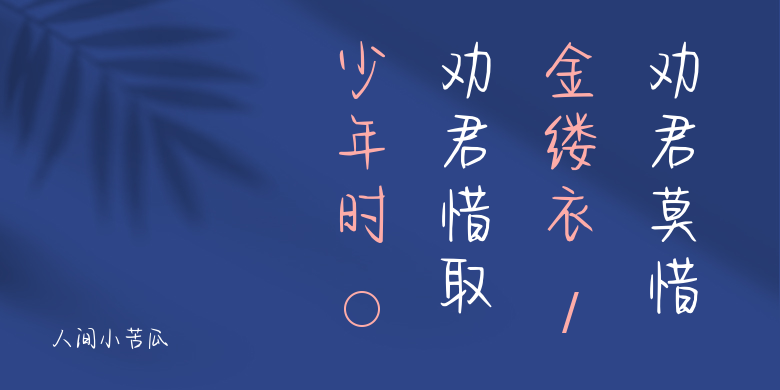
人间小苦瓜
人间小苦瓜,这款字体结构工整、笔画清晰,兼顾美观与易读性,适用于标题、正文、海报、包装、LOGO 等多种场景。字形优雅稳定,风格百搭耐看,适配日常排版与创意设计,让文字呈现更舒适、更具质感。人间小苦瓜一笔一画,皆是细节,以均衡的比例、流畅的线条打造舒适视觉体验,字形端正大气,风格简约现代。无论是商业设计、品牌宣传还是日常排版,都能轻松驾驭,让文字更有格调与力量。人间小苦瓜字体下载。